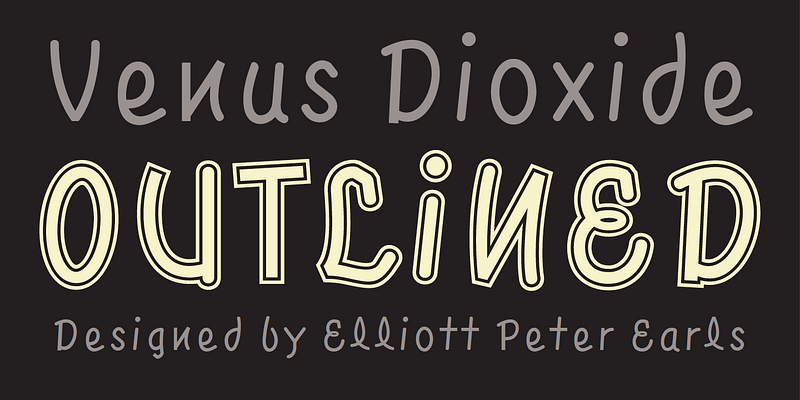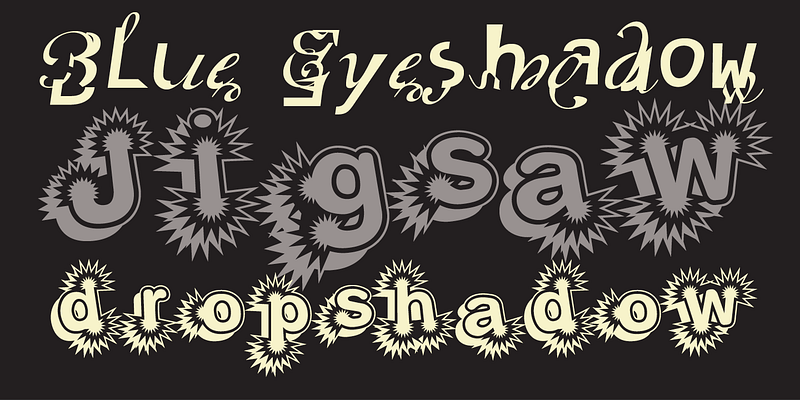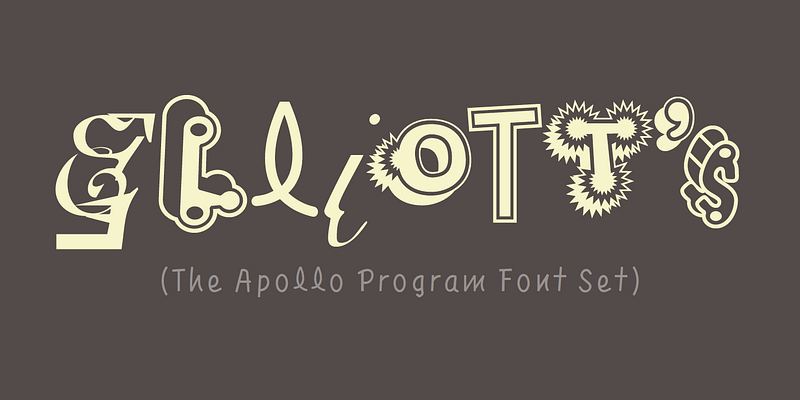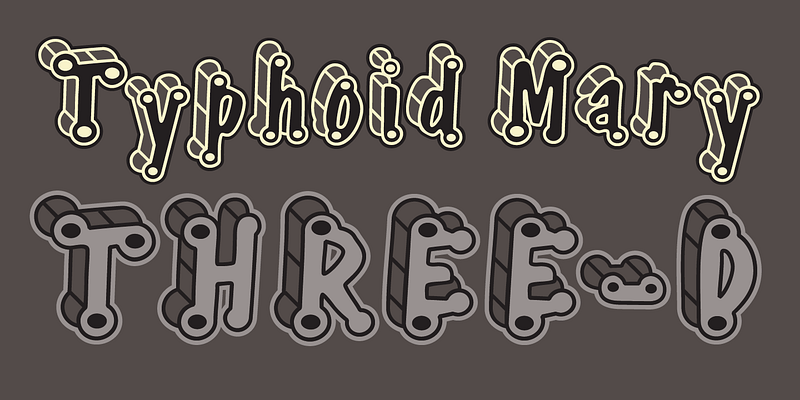
Questi sei caratteri disparati sfidano la classificazione o il confronto e sono meglio spiegati dalla seguente dichiarazione di Earls:
“Pensa a questi font come alla mia visione indotta da una stringa trovata sul mio tavolo, o alla mia Pieta, o alla mia rivoluzione notturna. La caricatura grottesca delle avanguardie del primo dopoguerra e la noia del poser-skatepunk veneziano sono gli strumenti a mia disposizione. Come il gonzo Karel Appel, che lanciava palle di cannone come un clown da circo contro la sua tela, anch’io dipingo come un barbaro in un’epoca barbarica. Sono completamente disinteressato all’eloquenza e alla profondità simulata che si trovano tra virgolette, ma per il bene del discorso ritualizzato, permettetemi di provarci citando Max Ernst: “Un pittore è perso se si ritrova“. Il fatto che sia riuscito a non ritrovare se stesso è considerato da Ernst come la sua unica conquista. Ben fatto. Anch’io apprezzo la soppressione della logica e i giochi di mezzanotte della dama cinese, ma a che scopo? Questa domanda attraversa il mio cervelletto come una peste bubbonica medievale, lasciando dietro di sé il fetore del relativismo e del pensiero post-utopico. Sono il triste figlio della tribù perduta delle scimmie ebola. Privato di diritti intellettuali, ambientali e finanziari.“